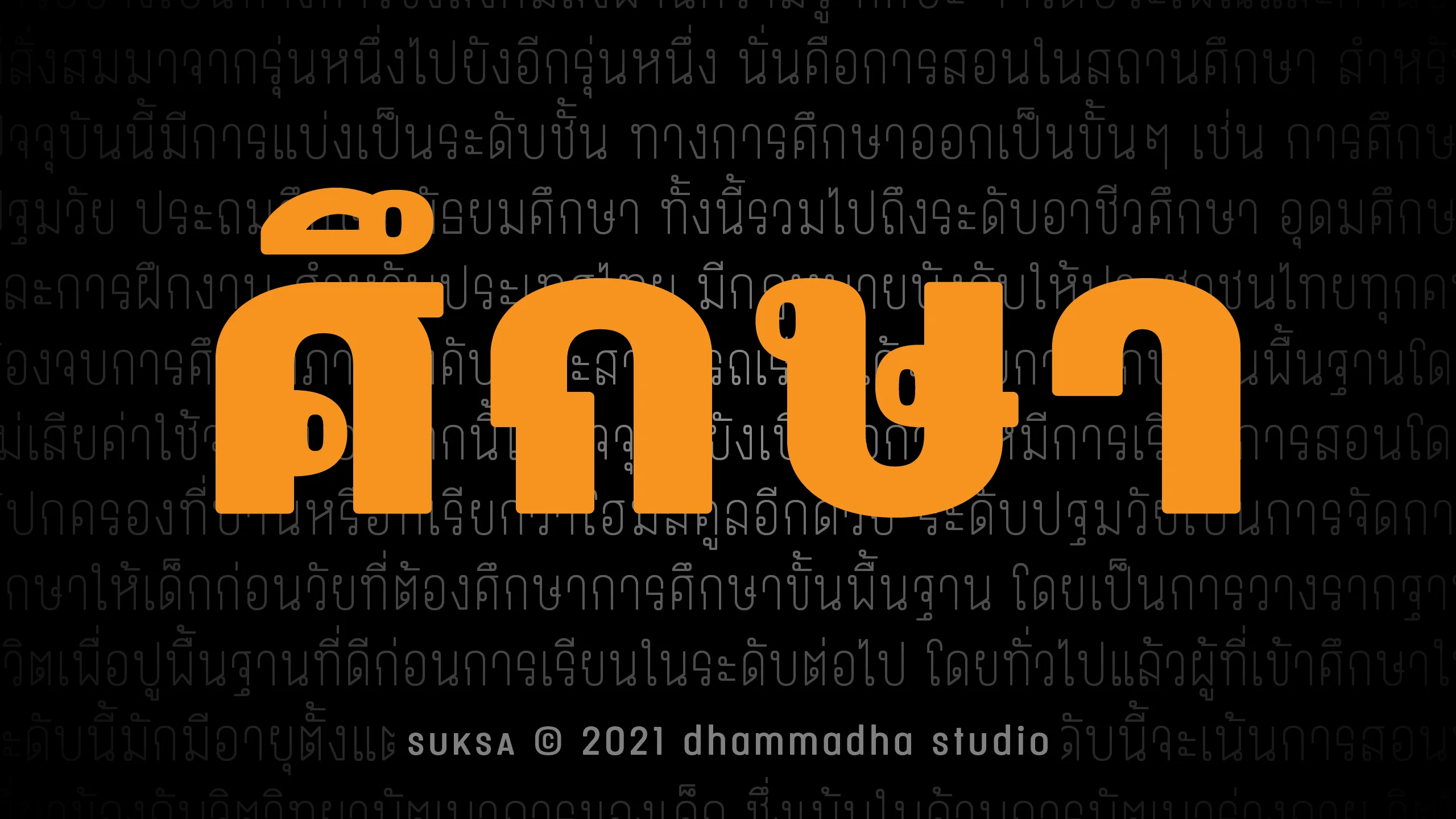
ชุดอักษรร่วมสมัยที่มาพร้อมกับบุคลิกอันโดดเด่นและเต็มเปี่ยมไปด้วยพลังในการสื่อสาร เราตั้งใจออกแบบให้ฟอนต์ชุดนี้มีความร่วมสมัยแต่ยังคงไว้ซึ่งความชัดเจน ด้วยการรักษาเอกลักษณ์ของอักษรไทยไว้อย่างครบถ้วน ทำให้ผู้อ่านสามารถรับรู้ข้อมูลได้อย่างแม่นยำและไม่สับสน เป็นการผสมผสานระหว่างงานดีไซน์ยุคใหม่เข้ากับโครงสร้างมาตรฐานที่ทำให้ตัวอักษรแต่ละตัวดูมีมิติและน่าจดจำ ด้วยความยืดหยุ่นในการใช้งานที่ครอบคลุม "ศึกษา | SUKSA" จึงตอบโจทย์ทั้งการทำหน้าที่เป็นฟอนต์พาดหัว (Display Font) ที่มอบความเท่และสะดุดตาในทันทีที่มอง หรือจะเลือกใช้เป็นฟอนต์เนื้อความ (Text Font) ก็ยังคงความเก๋ที่ดูสะอาดตาและอ่านง่ายในทุกย่อหน้า ไม่ว่าจะเป็นงานสร้างแบรนด์ที่ต้องการภาพลักษณ์ที่ดูเป็นมืออาชีพแต่เข้าถึงง่าย หรืองานกราฟิกที่ต้องการความเรียบเท่สไตล์มินิมอล ฟอนต์ชุดนี้จะช่วยให้งานของคุณดูสมบูรณ์แบบและสื่อสารตัวตนออกมาได้อย่างชัดเจนที่สุด